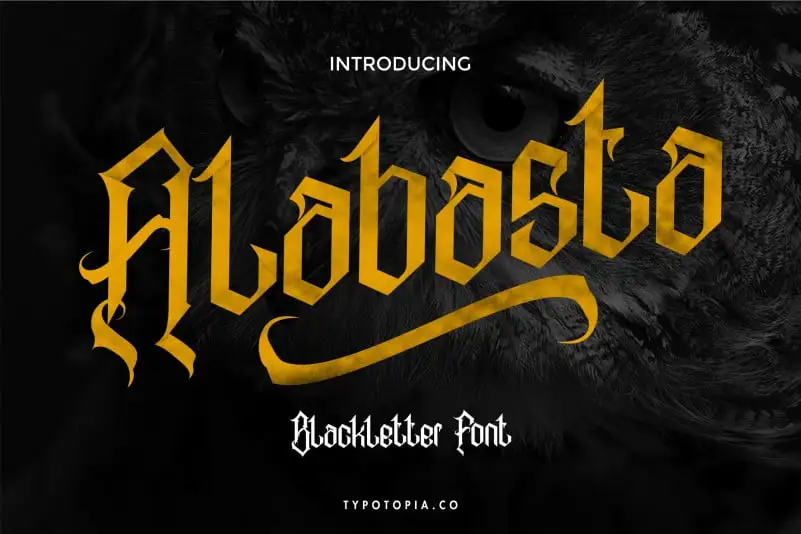
Alabasta Blackletter Font – Download Grátis
A Alabasta Blackletter é uma fonte única e distinta que se destaca no mundo das fuentes serifadas. Introduzida pelo designer typotopia, esta escolha para suas criações representa um estilo singular do caligrafista medieval conhecido como blackletter. Ideal para projetos que buscam criar um ar retrô ou clássico, a Alabasta Blackletter oferece uma ampla gama de caracteres, incluindo letras maiúsculas e minúsculas, pontuação e até mesmo caracteres internacionais. Este é um recurso adicional para designers gráficos que buscam criar ambientes visualmente intrigantes e distintos em seus projetos. A Alabasta Blackletter é uma ótima escolha para aqueles que procuram estilos antigos misturados com elementos contemporâneos, transformando qualquer design num verdadeiro trabalho de arte.